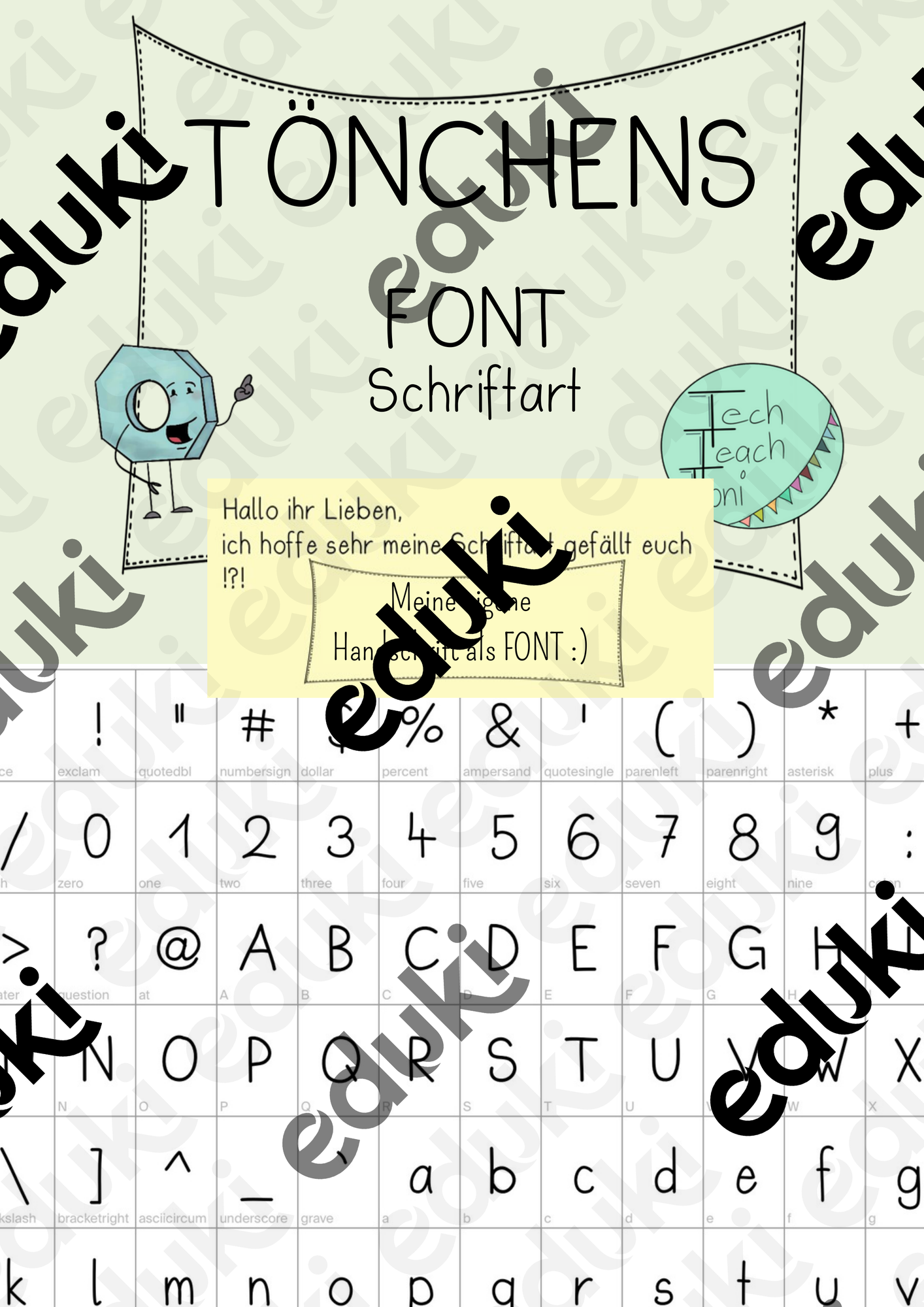
selbst erstellte Schriftarten - TönchensFont- Schriftart - Meine Handschrift als Font - TechTeachToni - Deckblatt
Ich habe euch meine Habndschrift digital aufbereitet, um sie euch zur Verfügung zu stellen!
TönchensFont- Schriftart - Meine Handschrift als Font